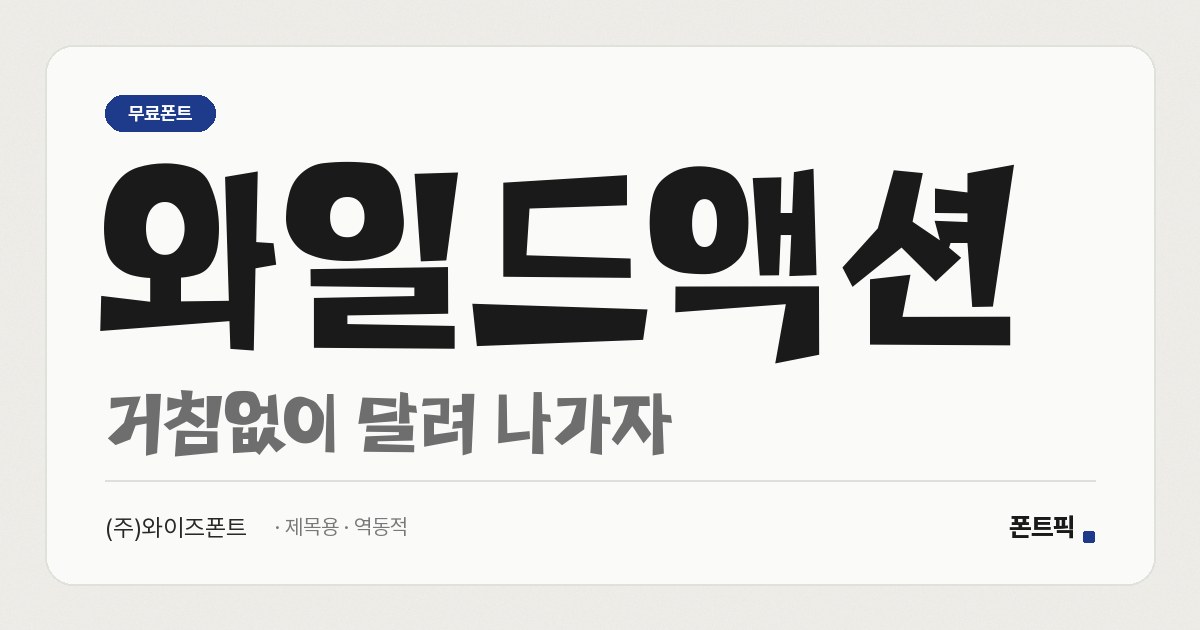
와일드액션
TDTDWildAction
- 굵기1종 Bold
- 분류제목용 · 역동적
TDTDWildAction
폰트 구독 서비스 타닥타닥을 운영하는 와이즈폰트가 직접 만든 제목용 서체입니다. 이름 그대로 움직임이 느껴지는 굵은 글자입니다.
획의 끝을 비스듬하게 잘라 내고, 기둥과 가로획을 자소마다 조금씩 다른 각도로 기울였습니다. 그래서 반듯한 네모틀 고딕과 달리 글자가 튀어 오르는 듯한 리듬이 생깁니다. 획이 아주 굵은데도 속공간이 막히지 않아, 받침이 많은 글자도 크게 쓰면 또렷하게 읽힙니다.
한글은 KS 완성형 2,350자에 자주 쓰는 430자를 더한 2,780자를 담았습니다. 그 밖의 글자는 빈칸으로 나오니, 드문 글자가 들어가는 문구는 미리 확인해 보세요. 영문·숫자·기본 문장부호도 들어 있고, 굵기는 Bold 하나입니다. 작은 본문보다는 썸네일, 포스터, 이벤트 배너의 한 줄 제목처럼 크게 쓰는 자리에 어울립니다.